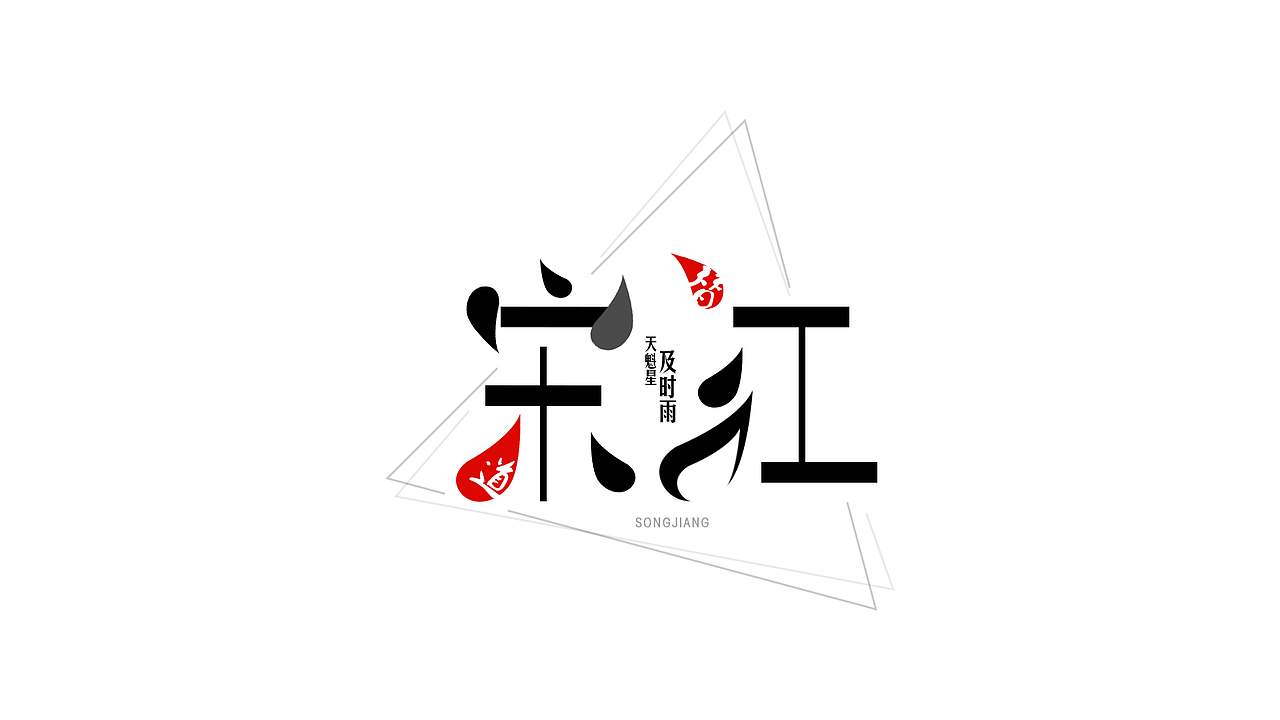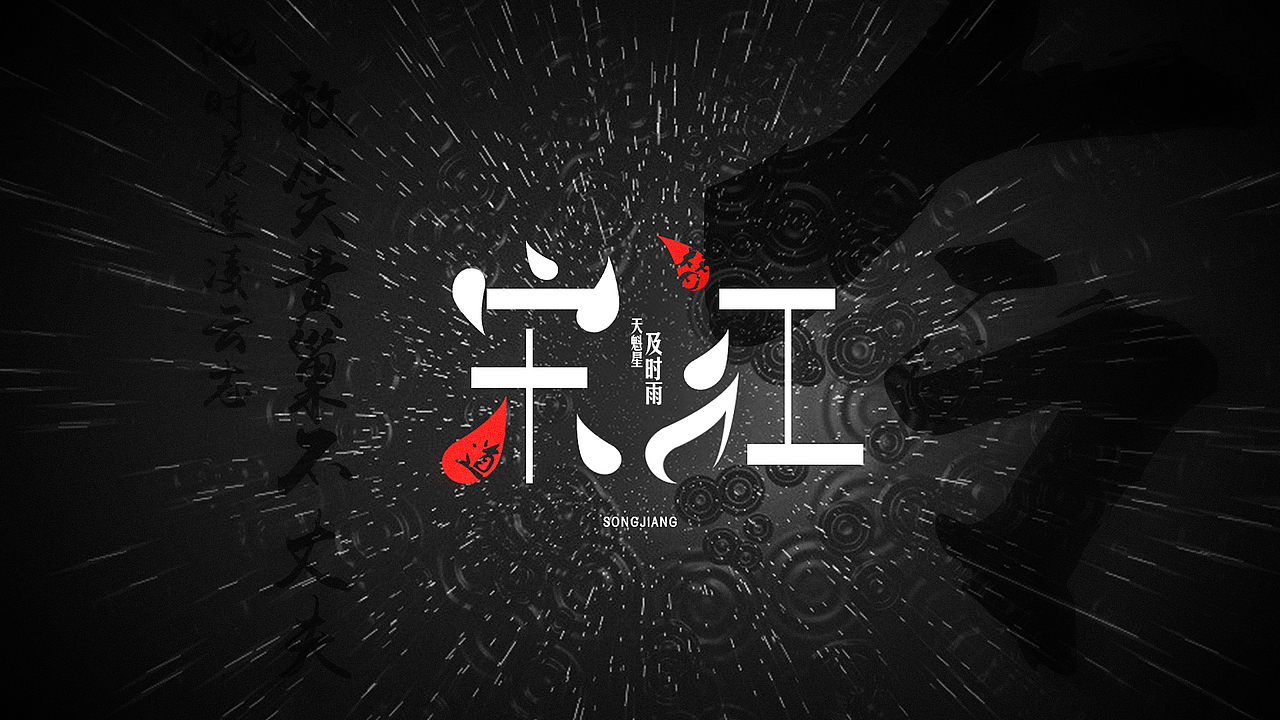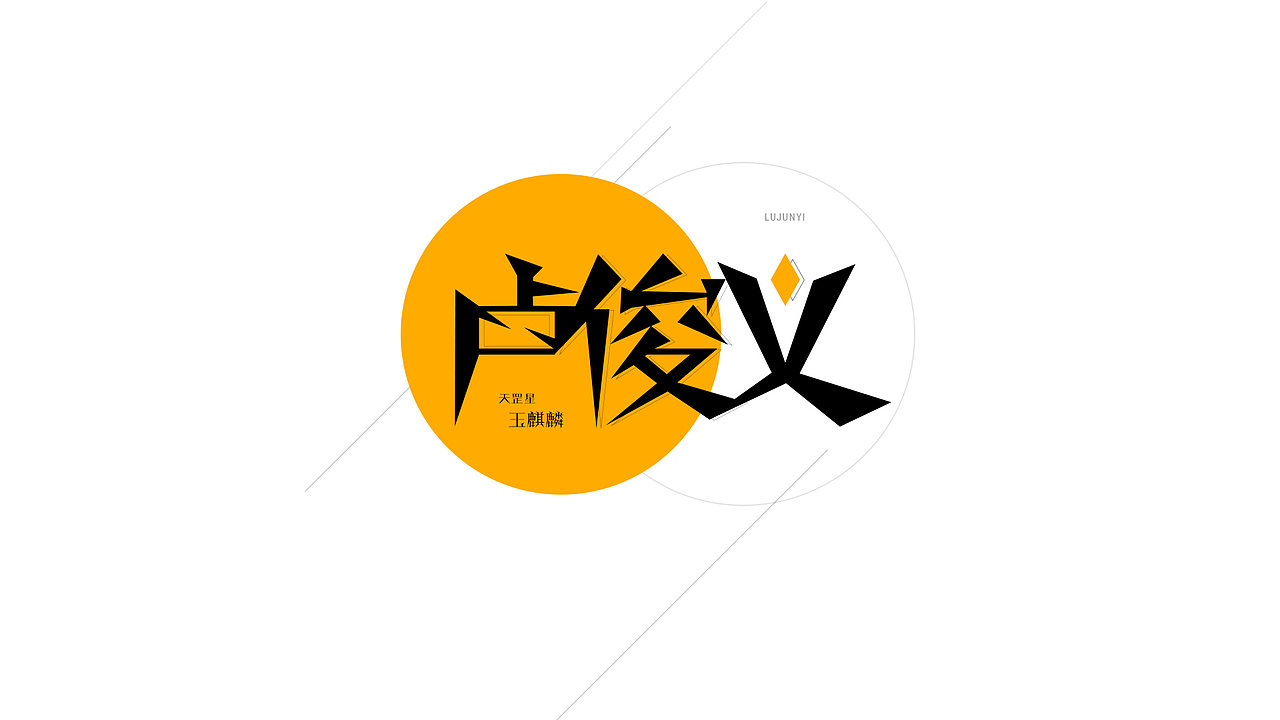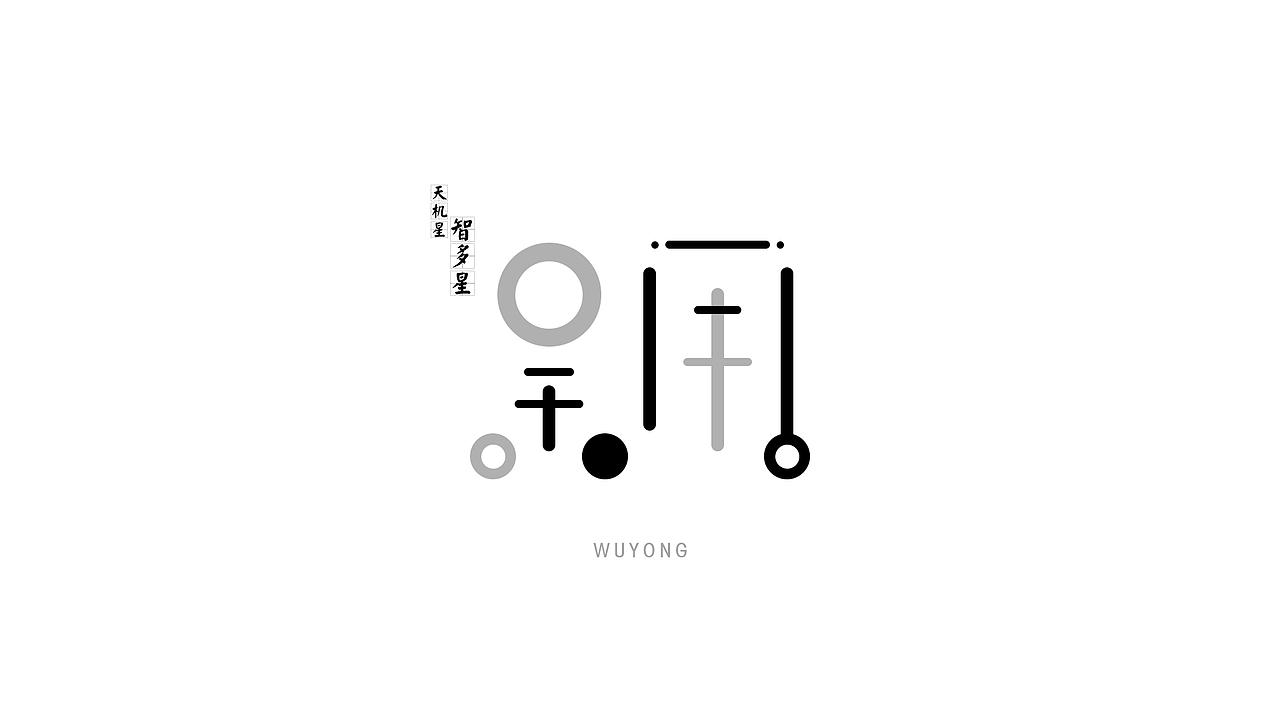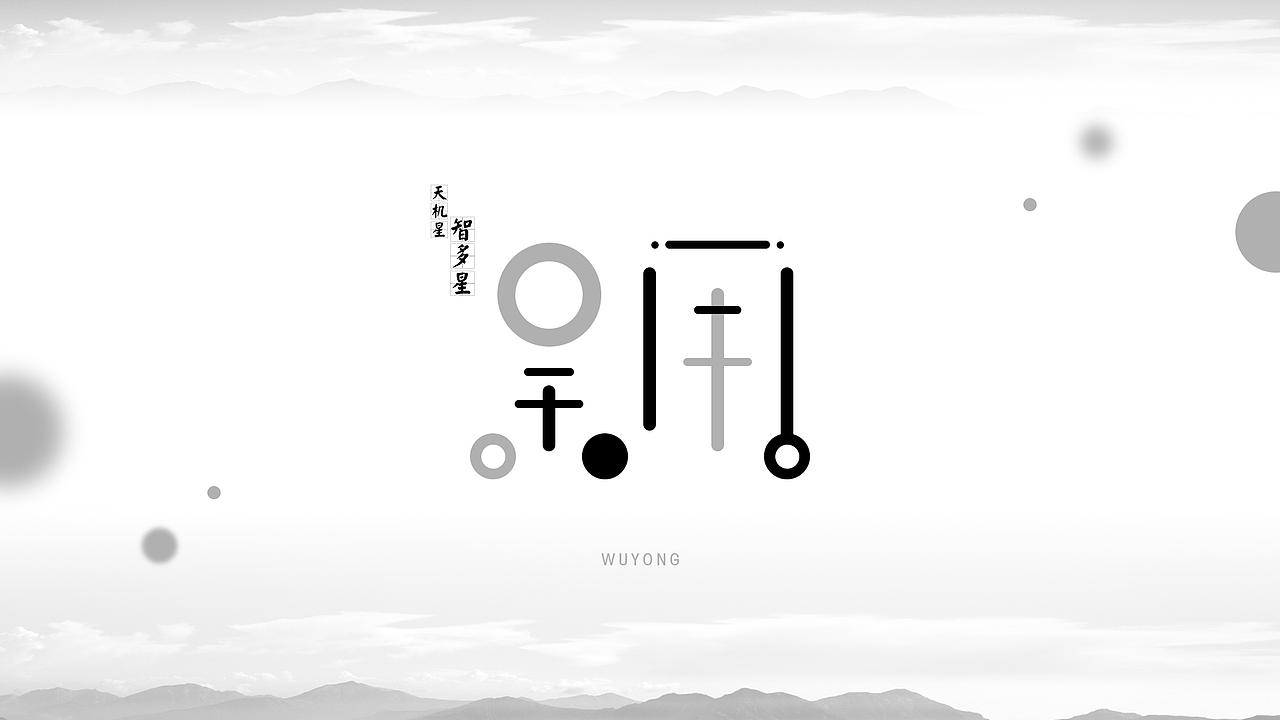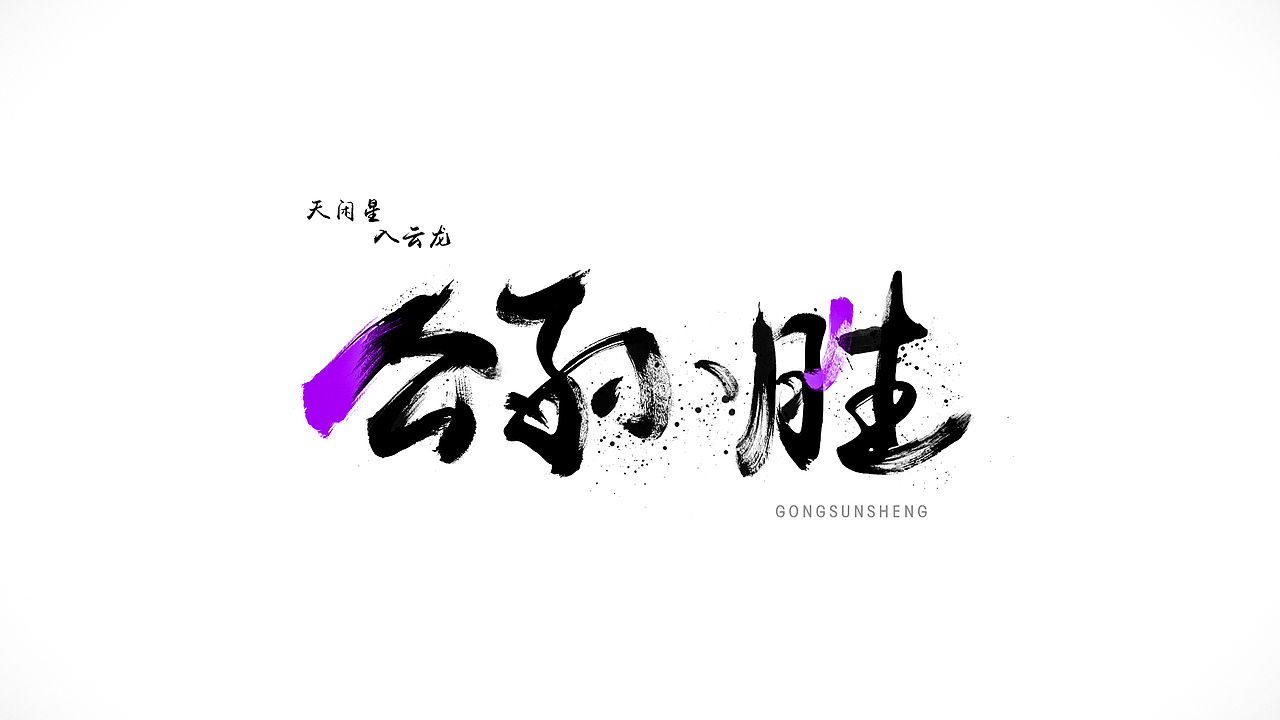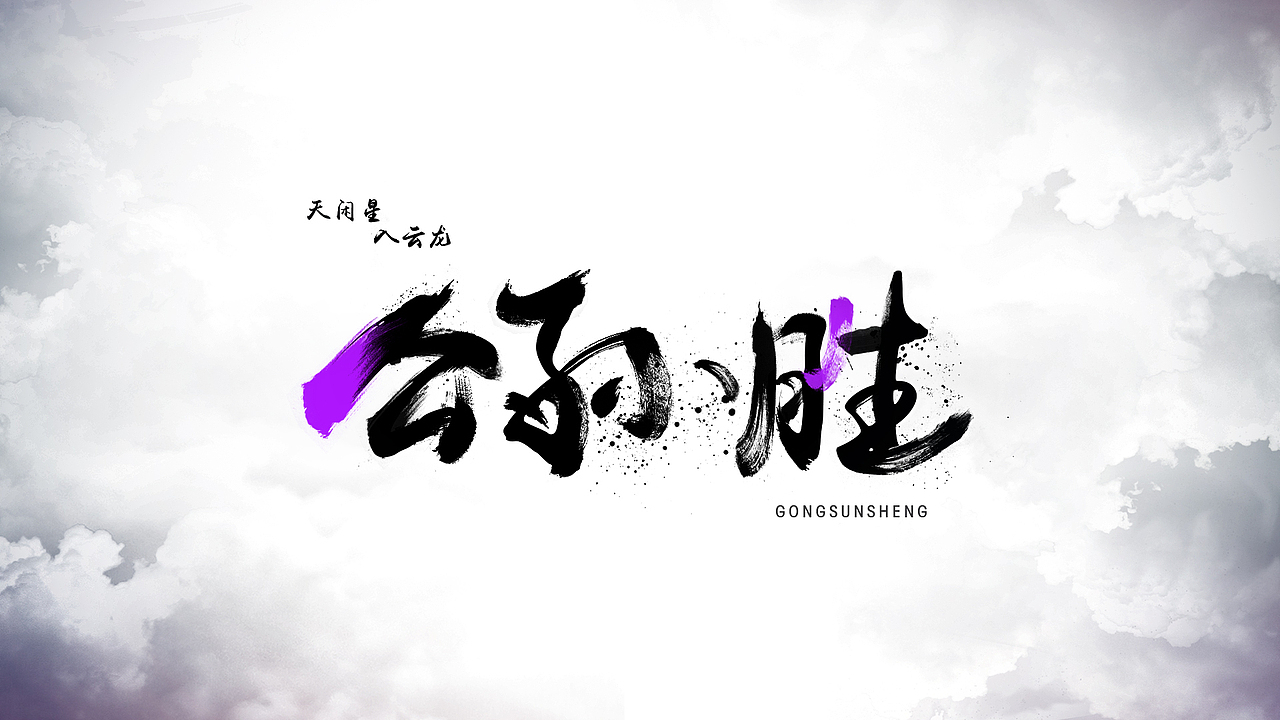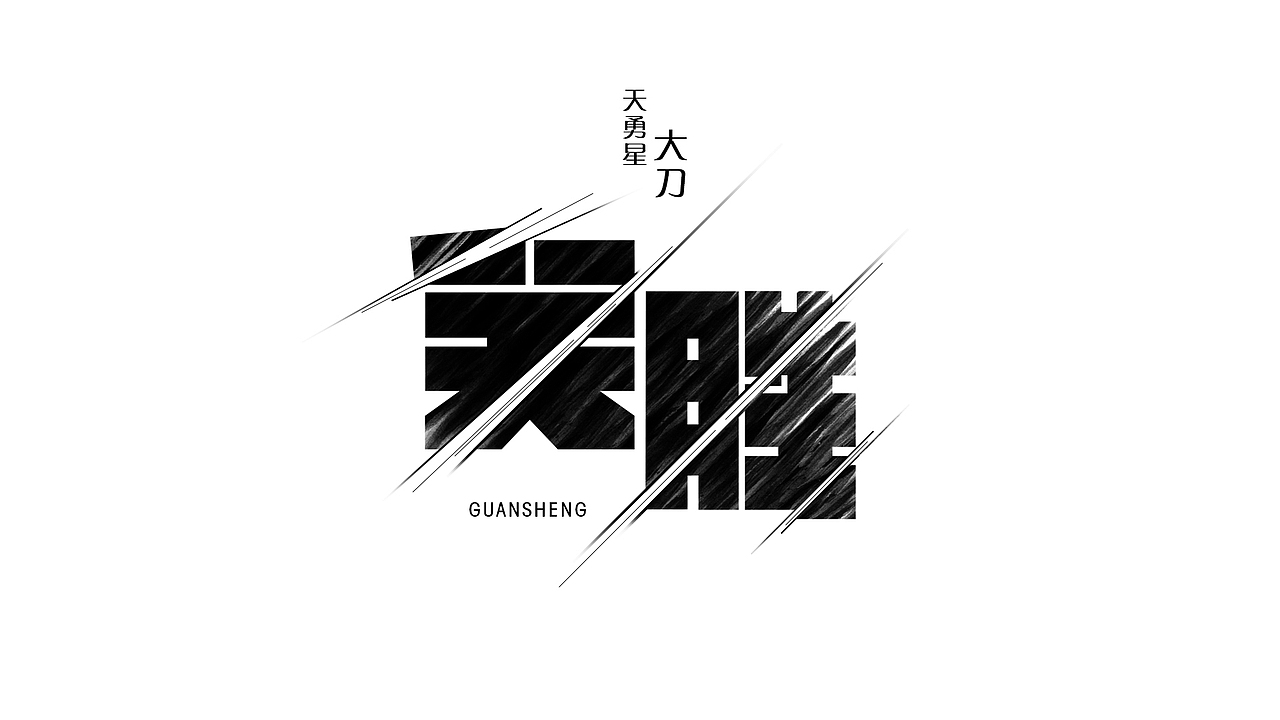
水浒中的那些人(1)
上小学的时候父亲给买了水浒传的连环画(朝鲜文版,一本不到1块钱。。。),一发不可收拾的深深迷恋于其中的人物与故事中,看了几十遍,如今还保管着当年的书籍。长大后慢慢开始读正规的全本,从故事中寻找故事,从人物中理解人物,只能说这是一部越读越让人有思考的著作。
【1】及时雨——宋江
想法来源——及时雨、替天行道(未完成)、号令、矛盾性格、反诗——他时若遂凌云志,敢笑黄巢不丈夫。
【2】玉麒麟——卢俊义
想法来源——麒麟、天下无双、刚毅勇猛、希望。
【3】智多星——吴用
想法来源——学究、性格圆润、服侍二人(晁盖、宋江)性格迥异、自缢身亡。
【4】入云龙——公孙胜
想法来源——道长、入云、法术、满腔抱负。
【5】大刀——关胜
想法来源——大刀、忠烈、刚正。
【6】豹子头——林冲
想法来源——风雪、上山、枪棒、刺配、枯竭。
【7】霹雳火——秦明
想法来源——霹雳火、火爆性格、狼牙棒、惨死。
【8】双鞭——呼延灼
想法来源——双鞭、连环马、七星皂罗袍、踢雪乌骓马、血气方刚。
【9】小李广——花荣
想法来源——花美男、箭术、义气。
【10】小旋风——柴进
想法来源——旋风、皇孙。